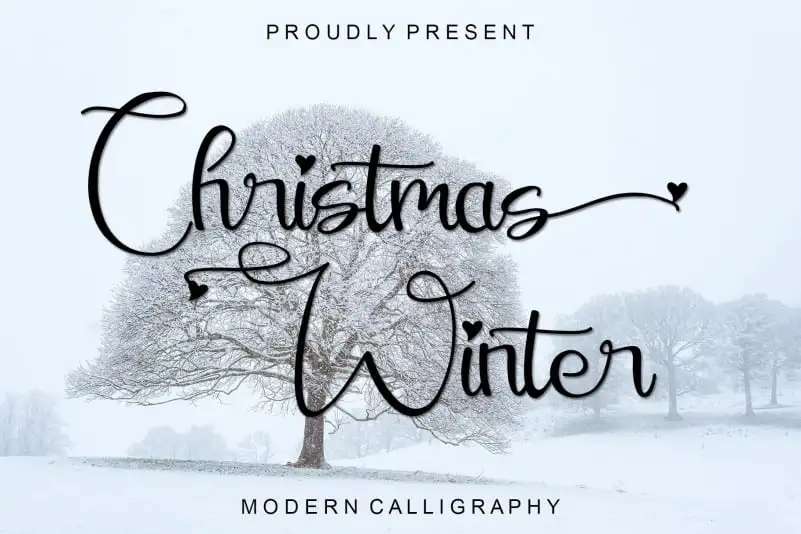
Christmas Winter Calligraphy Font – Download Grátis
A fonte ‘Christmas Winter Calligraphy Font’ é ideal para aqueles que buscam uma fonte perfeita para trabalhos criativos nessa época do ano. Esta elegante e fluida fonte, desenvolvida pelo designer Ahmad Afandi de 99designs, é especialmente adequada para projetos como casamentos, blogs pessoais ou redes sociais. Ela traz um estilo simples mas poderoso que faz com que qualquer design seja imediatamente atraente. Com suas ligaturas e swashes personalizadas, esta fonte permite uma facilidade incomparável na escrita de texto chamigrafia. É perfeitamente projetada para utilização em designs como casamentos, cartões de cumprimentos ou anúncios, sem mencionar que é um excelente complemento para qualquer projeto design atual. Ideal tanto para iniciantes quanto para profissionais experientes, a ‘Christmas Winter Calligraphy Font’ traz uma beleza única e um toque especial à sua próxima criação visual. Não perca a oportunidade de enriquecer seus trabalhos com esse belo e versátil complemento de fonte.